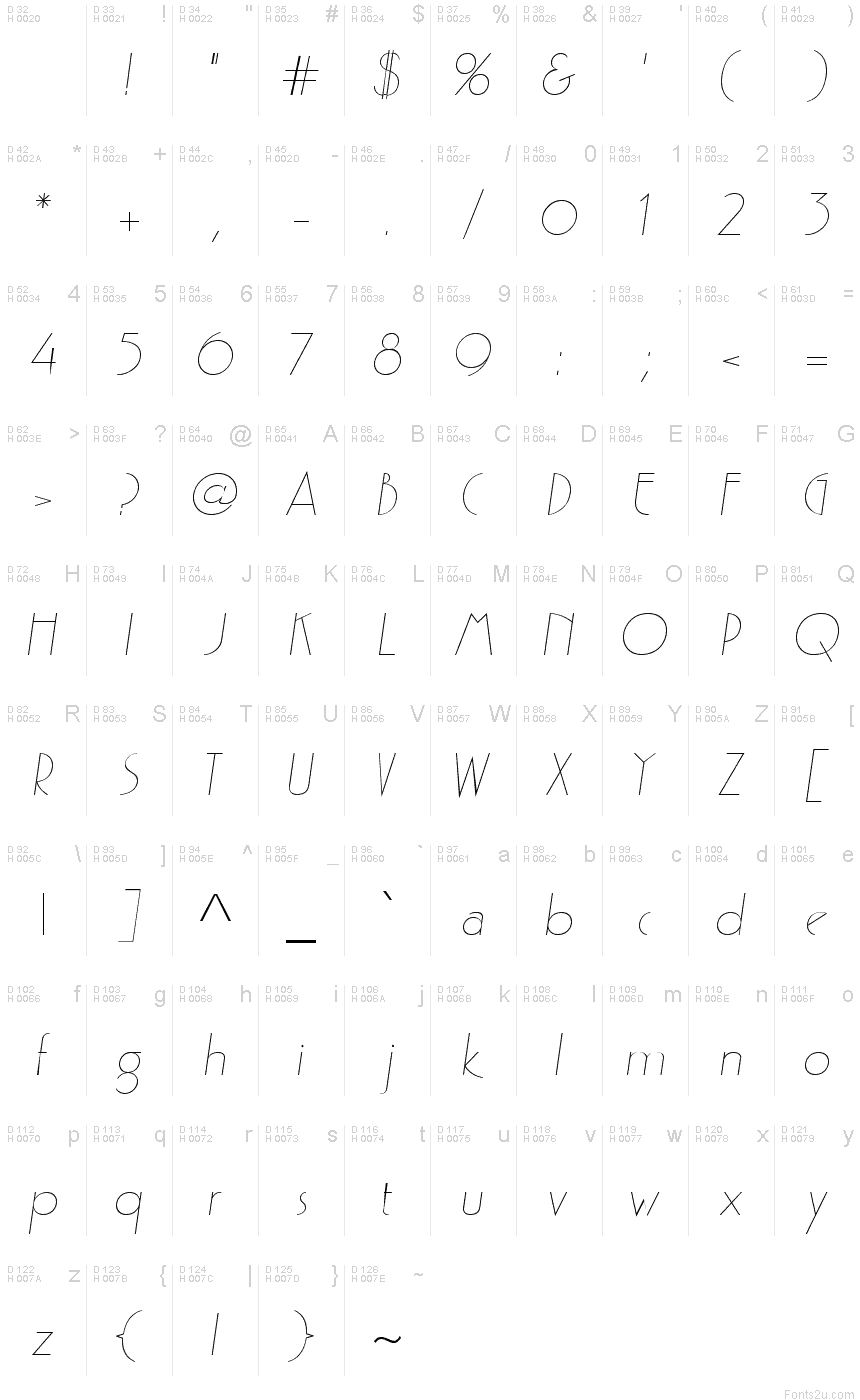
Zelda Italic
Zelda Italic, darmowy, geometryczny krój bezszeryfowy od Br0derbund Software, nawiązuje do chłodnego, cyfrowego modernizmu lat 90. dzięki bardzo cienkim liniom i wyrazistemu, pochylonemu rytmowi. Litery są przewiewne i lekko nakreślone, z szeroko otwartymi łukami i niemal schematyczną prostotą, co nadaje im elegancki, a nie ekspresyjny wygląd.
Ten bezpłatny font sprawdza się wszędzie tam, gdzie tytuł potrzebuje lekkiego, futurystycznego akcentu – w brandingu w stylu oprogramowania, na okładkach płyt, w lookbookach modowych, nagłówkach magazynów czy na planszach tytułowych. Pasuje również do krótkich nazw na opakowaniach i nagłówków stron, ponieważ wąskie pochylenie i oszczędna linia nadają nawet prostym słowom pewny, techniczny charakter.